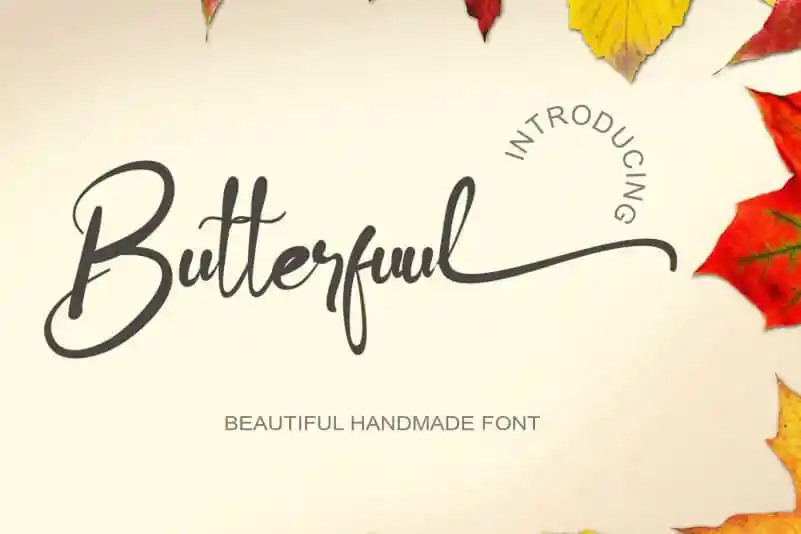
Butterfuul Calligraphy Font – Fonte Grátis
Butterfuul Calligraphy Font
A ‘Butterfuul Calligraphy Font’ é uma fonte escrita à mão simples e adaptável que oferece belos caracteres equilibrados, tornando-a perfeita para um amplo range de designs. Suas características elegantes e bem balanceadas fazem dela um tesouro para quem procura personalidade em seu trabalho gráfico. Crie designs espectaculares com este estilo versátil e único. Aproveite a liberdade criativa que esta fonte proporciona, seja você um designer de logotipo ou criação de materiais digitais. Adquira ‘Butterfuul Calligraphy Font’ para revolucionar suas próximas criações de design.